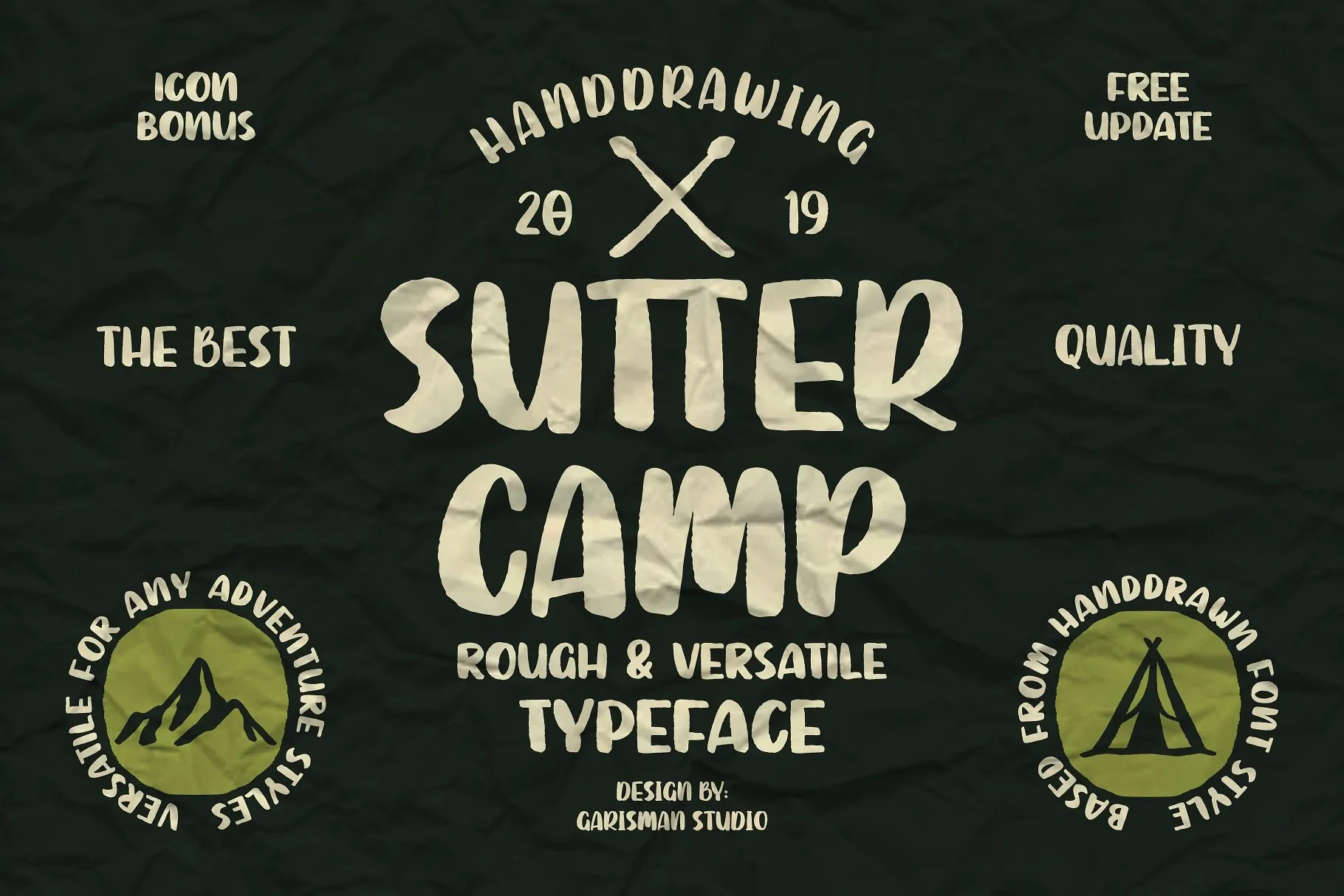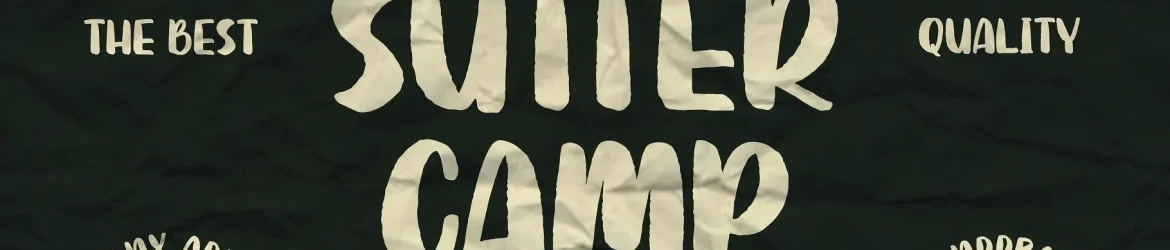
SUTTER CAMP Typeface – Download Grátis
SUTTER CAMP é uma fonte display que surgiu a partir de uma inspiração na atmosfera de aventura e natureza selvagem, com base em uma traço leve produzido por um especializado pincel. Esta fonte foi criada pelo designer M.0Type para fontes users que apreciam o estilo aventuroso e desenhado a mão. Com sua textura suave de caneta e linhas grossas robustas, SUTTER CAMP se destaca como uma opção ideal tanto para quem busca um novo estilo de escrita quanto para quem adora o design gráfico criativo e realista da natureza. Com seu toque casual de caneta artesanal e linhas rústicas, a fonte não apenas transmite um senso de aventura ao texto, mas também uma conexão com o mundo natural que a inspirou. Isso torna SUTTER CAMP uma opção perfeita para aqueles que buscam adicionar mais vida à sua composição visual, seja no design de gráficos ou em materiais publicitários.